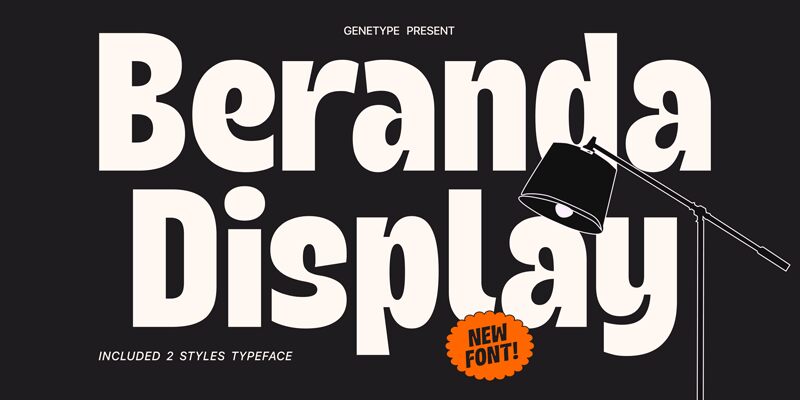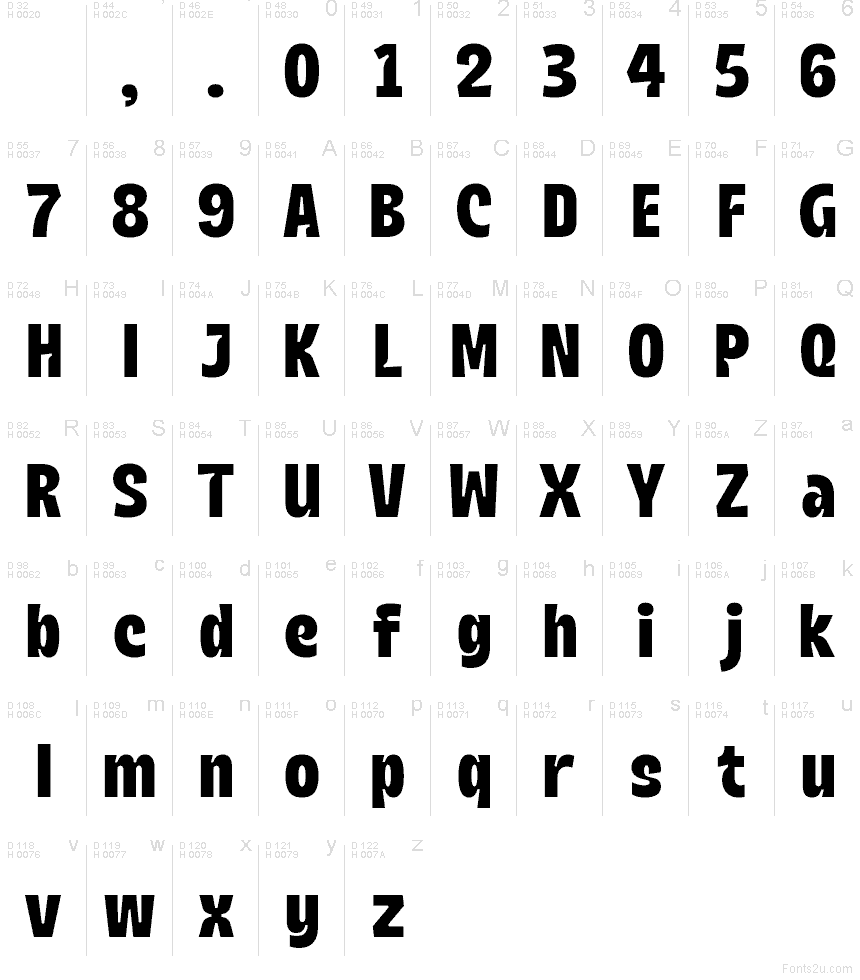
Beranda, creata da Bagus Arya Kirana di Genetype, possiede un carattere amichevole e corposo, caratterizzato da tratti arrotondati e tagli giocosi che ricordano quasi l'effetto di un timbro in gomma. È audace senza essere eccessiva, mantenendo una forma coerente e leggibile anche a una prima occhiata. Essendo un font sans serif gratuito, il ritmo vivace di Beranda conferisce ai titoli un tocco caldo, moderno e un po' retrò.
Usa Beranda per loghi, menu di bar, confezioni di snack, titoli di poster, annunci social, sticker e merchandising laddove desideri fascino e leggibilità immediata. Questo font gratuito brilla anche sulle schermate di avvio delle app e sui volantini per eventi, specialmente se utilizzato in grandi dimensioni con una spaziatura generosa. Abbinalo a una sans neo-grotesca pulita e leggera per il testo principale, così da mantenere un contrasto netto.